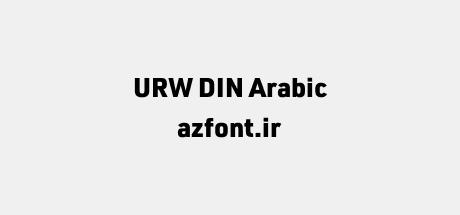
URW DIN Arabic
فونت زیبای رایگان URW DIN Arabic
قلم زیبای URW DIN Arabic Black از سری قلم های بسیار زیبا برای تایپوگرافی و لوگو تایپ می باشد.این قلم در وزن Black و توسط ar.photoshop.3abber.com طراحی و منتشر شده است.